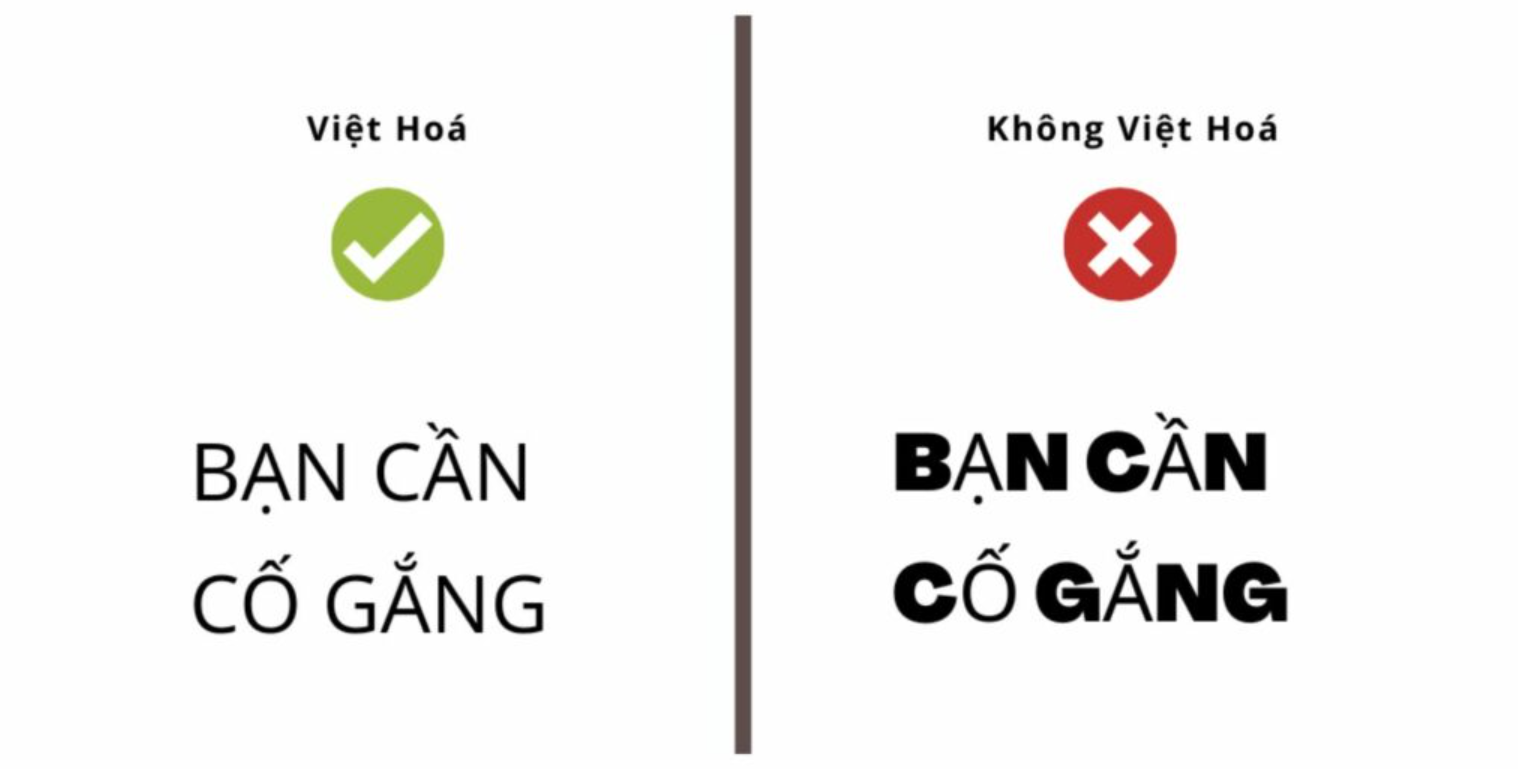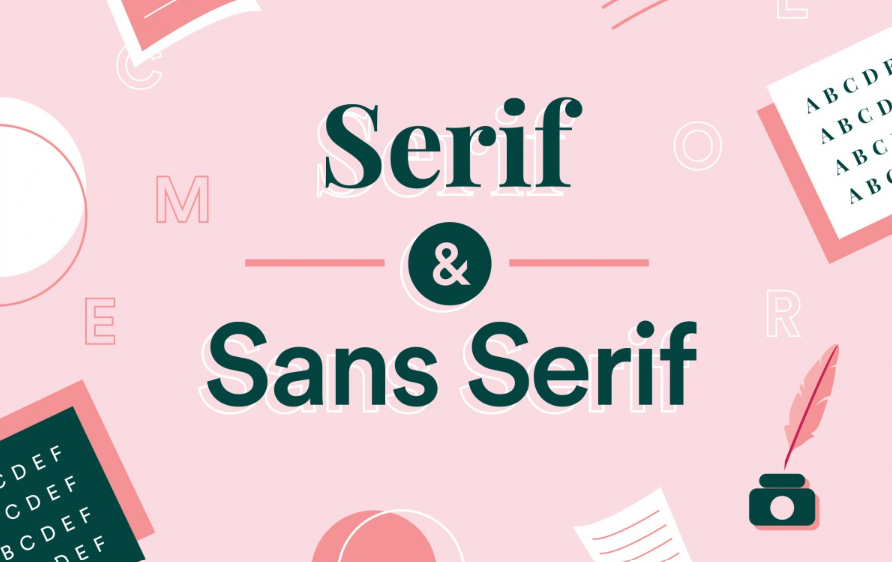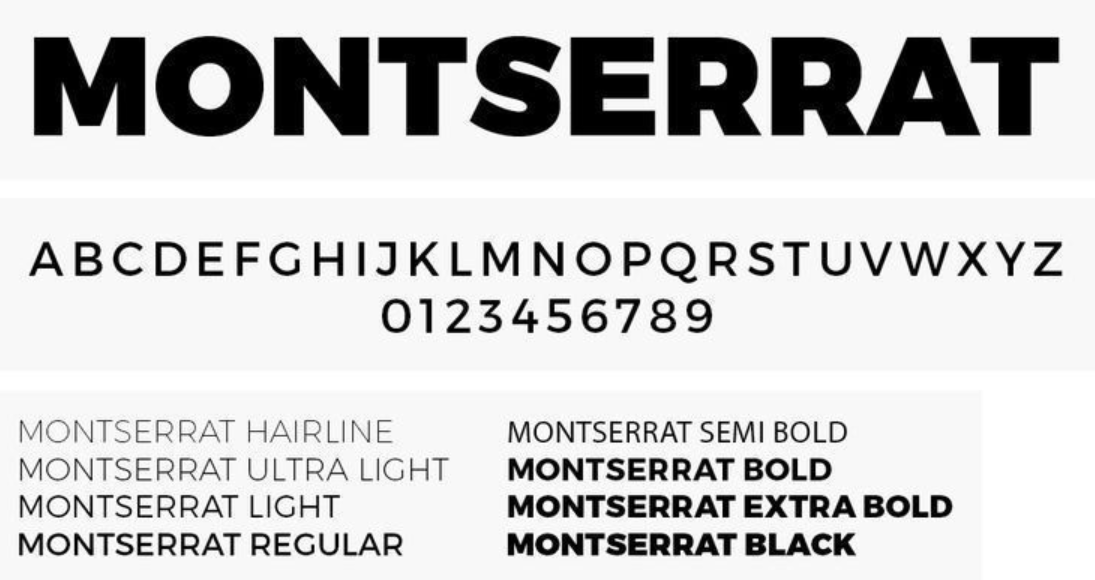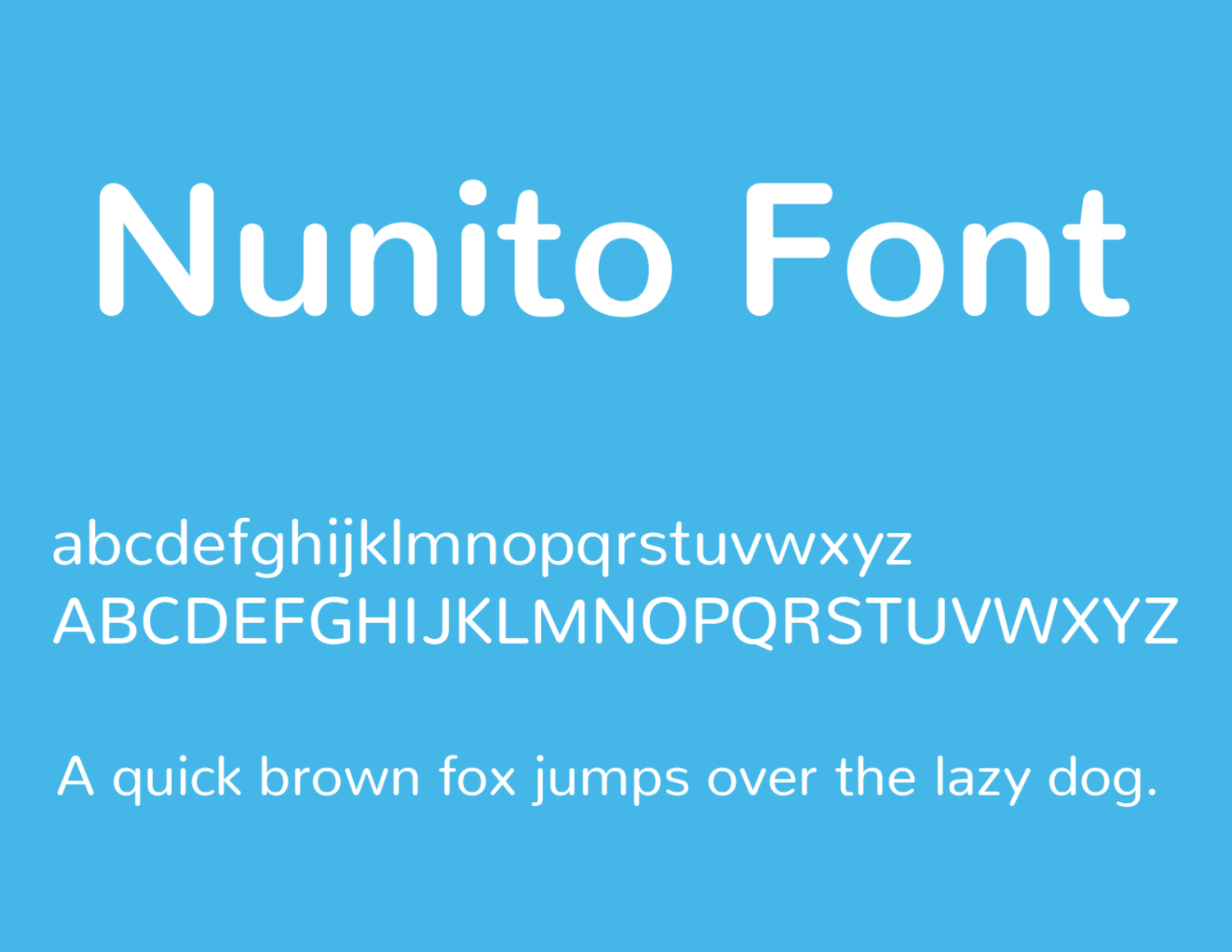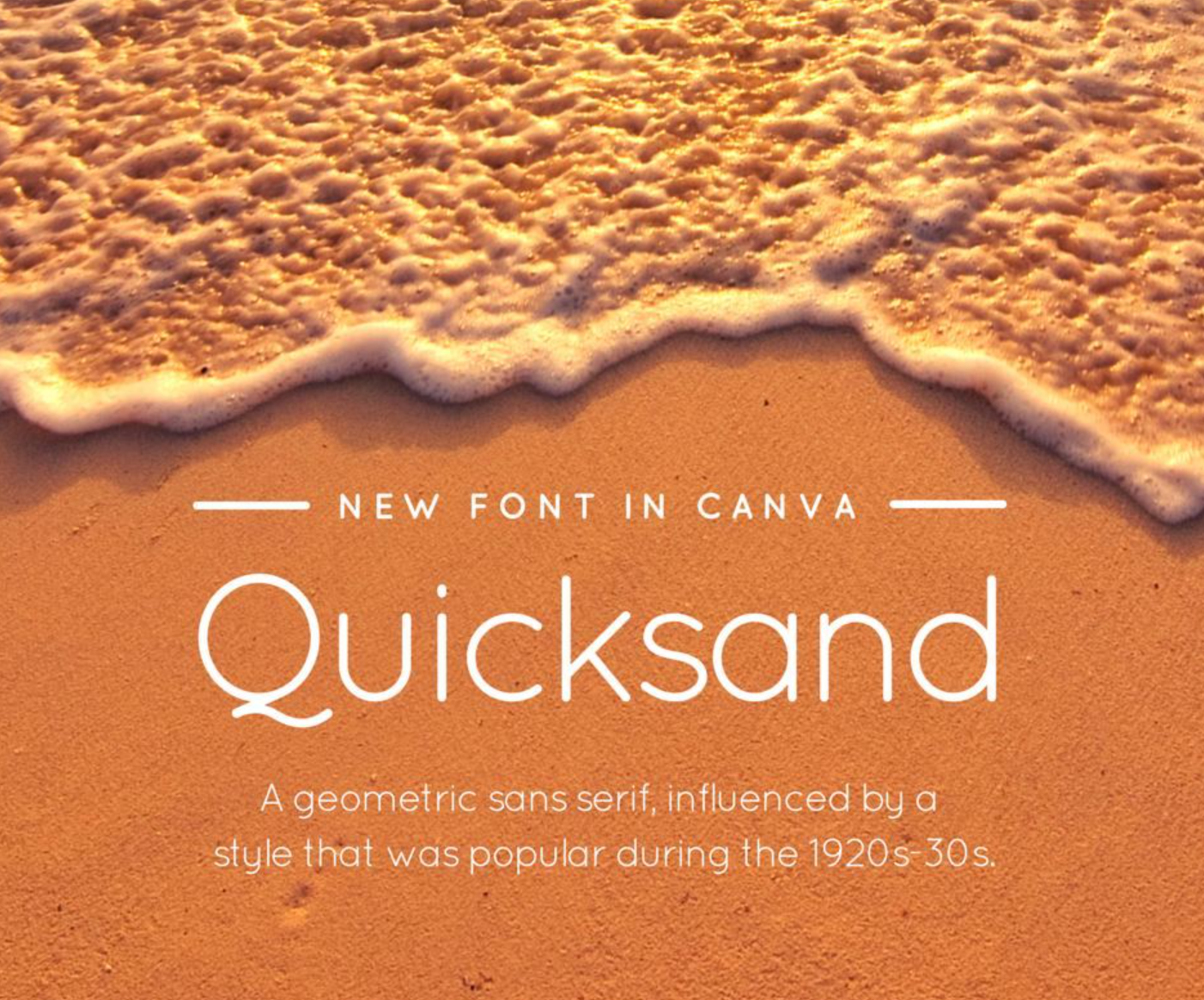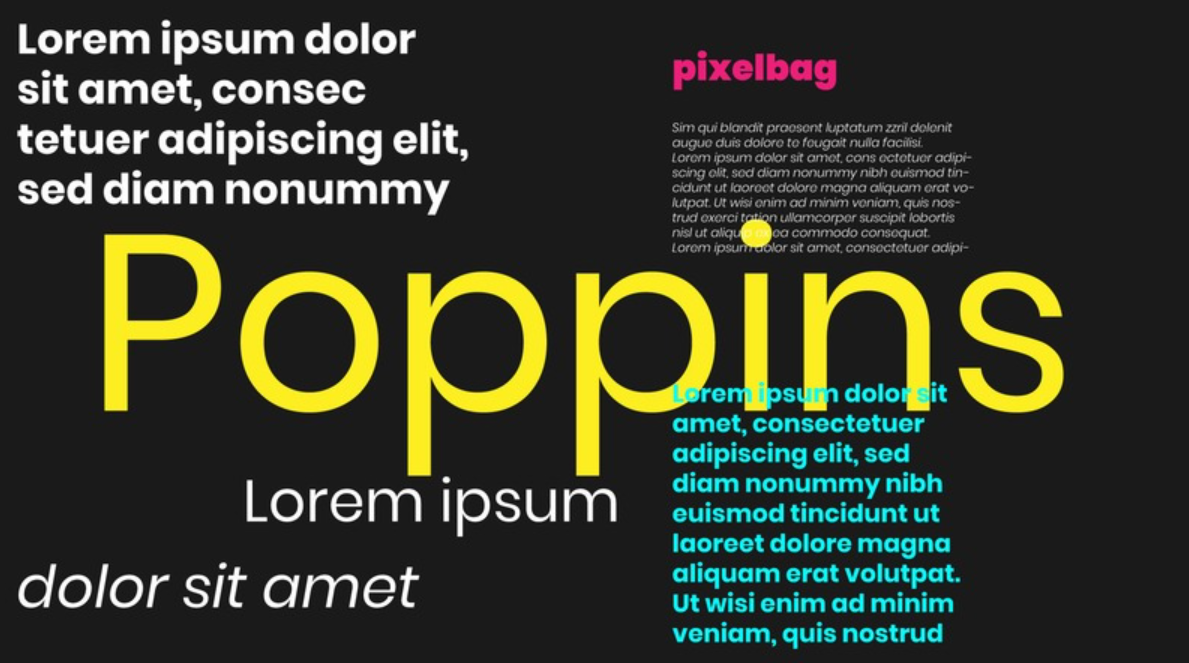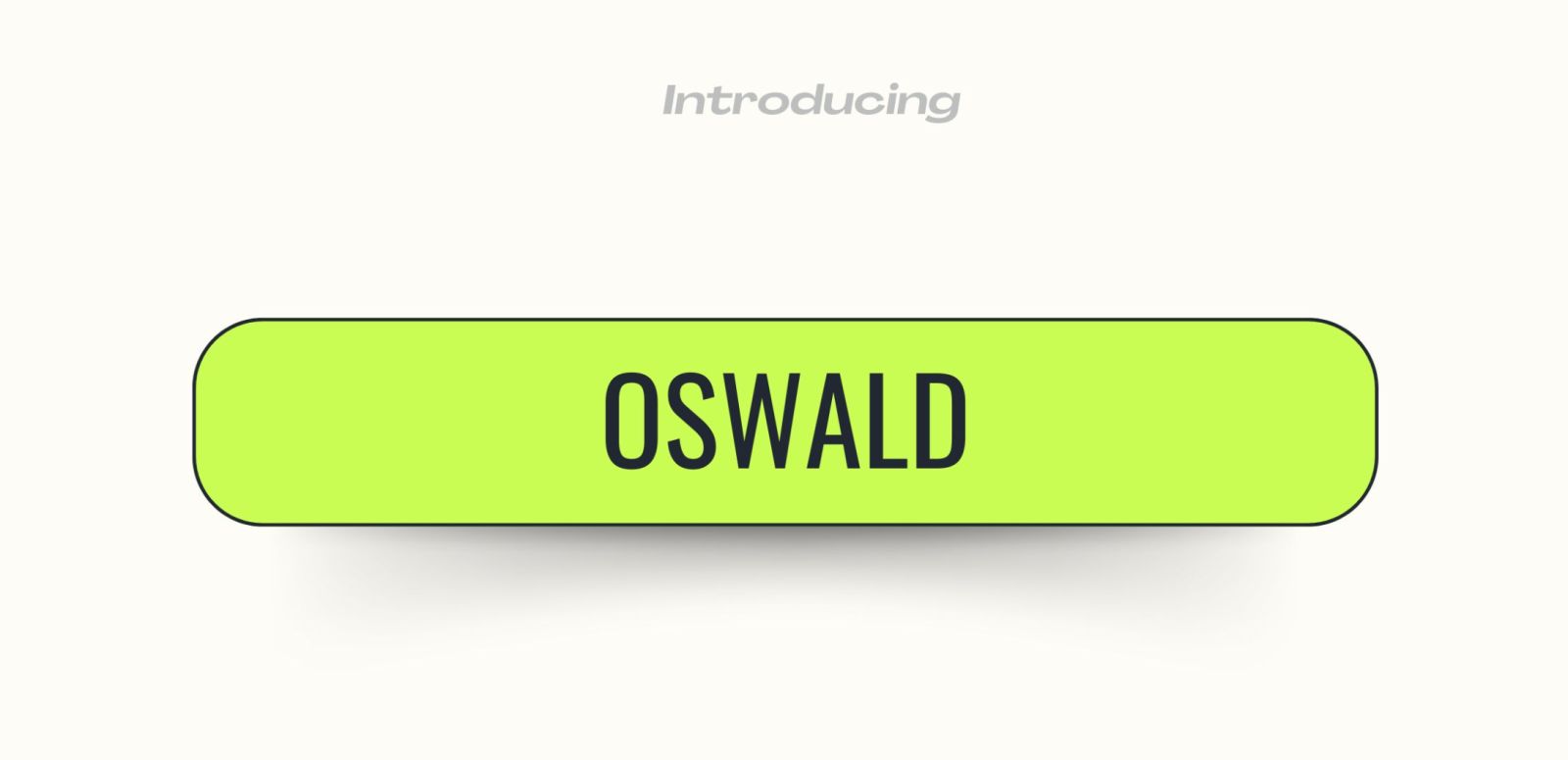
Khám Phá Kho Font Việt Hóa Miễn Phí Trên Canva
Bạn có biết rằng Canva cũng có rất nhiều phông chữ đẹp trên canva và phù hợp để bạn lựa chọn? Nếu bạn chưa biết, hãy cùng SaDesign khám phá những font chữ Việt hóa trên Canva trong bài viết này.
Bạn đang thiết kế trên Canva nhưng loay hoay mãi vì không tìm được font chữ hỗ trợ tiếng Việt đẹp mắt, đúng “gu” thẩm mỹ? Đừng lo! Việc tìm kiếm font Việt hóa miễn phí trên Canva giờ đây không còn là nỗi trăn trở như trước. Trong bài viết này, SaDesign sẽ giúp bạn tổng hợp những font chữ Việt hóa chất lượng cao, hoàn toàn miễn phí và có thể sử dụng trực tiếp trên Canva. Hãy cùng khám phá ngay để chọn được font chữ ưng ý, giúp thiết kế của bạn trở nên nổi bật, truyền cảm hứng và thể hiện đúng tinh thần bạn mong muốn nhé!
1. Font việt hóa khác gì so với font chưa việt hóa trên Canva ?
Khi làm việc với Canva, việc lựa chọn font chữ phù hợp cho tiếng Việt có thể trở thành một nhiệm vụ không dễ dàng.
Sự khác biệt giữa font chữ Việt hóa và font chữ chưa Việt hóa không chỉ ở khía cạnh thẩm mỹ mà còn ảnh hưởng đến tính đọc được và chất lượng của thiết kế.
Font việt hóa Canva
Font chưa việt Hóa
Đã được điều chỉnh và tùy chỉnh để hỗ trợ đầy đủ các ký tự và dấu trong tiếng Việt.
Font chữ không được thiết kế để hỗ trợ tiếng Việt.
Giúp thiết kế trở nên mượt mà và chuyên nghiệp.
Khi sử dụng có thể gặp phải vấn đề trong việc hiển thị các chữ cái có dấu.
Hỗ trợ đầy đủ ký tự tiếng Việt, thể hiện đúng ý muốn của người thiết kế, mang tính thẩm mỹ cao.
Thích hợp cho việc thiết kế văn bản tiếng Anh hoặc các ngôn ngữ không dùng dấu.
Số lượng font chữ Việt hóa có thể hạn chế, đòi hỏi tìm kiếm và cài đặt từ nguồn đáng tin cậy.
Không hỗ trợ đầy đủ ký tự tiếng Việt, gây rối và mất tính thẩm mỹ trong việc hiển thị văn bản tiếng Việt.
2. Mẹo sử dụng Sans Serif & Slab Serif để tìm Font chữ đẹp trên Canva
Để tìm được font chữ đẹp trên Canva, bạn nên dùng cặp từ khóa Sans Serif & Slab Serif khi tìm kiếm để nhanh chóng tìm được font chữ phù hợp:
Serif: Thường được biết đến với tên gọi “chữ có chân”, với các nét nhỏ ở cuối mỗi chữ. Chúng mang tính cổ điển và thường được sử dụng trong văn bản trang trọng hay sách giáo trình.
Sans Serif: Loại font này không có các “chân” ở cuối mỗi chữ, tạo nên vẻ ngoại hình mượt mà và hiện đại. Rất phù hợp với các thiết kế sáng tạo và trẻ trung.
Điều này giúp lọc ra các kiểu font chữ theo phong cách bạn muốn, từ đó tìm thấy các font phù hợp nhanh chóng.
Ngoài ra, đừng ngần ngại thử nghiệm nhiều kiểu font khác nhau trên bản thiết kế của bạn. Canva cho phép thay đổi font chữ một cách dễ dàng, vì vậy hãy thử nghiệm từng font một để xác định được font nào là phù hợp nhất.
3. Top font chữ tiếng việt đẹp trên canva mà bạn nên thử
Dưới đây là gợi ý các font việt hóa Canva đẹp được nhiều người yêu thích:
Montserrat: được thiết kế với đường nét chắc chắn, cân xứng, giúp font chữ này trở nên cứng cáp và dễ đọc. Phù hợp cho việc thiết kế banner hay truyền tải thông điệp một cách rõ ràng.
Nunito: với đường nét tròn trịa và mềm mại, rất thích hợp cho việc trình bày nội dung trực quan hoặc các sản phẩm dành cho trẻ em.
Lato: mang đến sự thanh thoát và tinh tế qua đường nét cân đối và chắc chắn của mình. Lato đặc biệt phù hợp cho bao bì sản phẩm, tiếp thị hoặc các ấn phẩm chuyên nghiệp.
Oswald: nổi bật với phong cách hiện đại mang hơi hướng cổ điển, đây là lựa chọn hoàn hảo cho tiêu đề bài viết, poster,… hoặc nơi bạn muốn tạo dấu ấn mạnh mẽ
Poppins: sở hữu đường nét rõ ràng và đều đặn, mang đến một phong cách thanh lịch và hiện đại. Font này được ưa chuộng trong việc thiết kế slide, trang web và ứng dụng trên điện thoại.
Quicksand: với phong cách đặc trưng là nhẹ nhàng và phóng khoáng, rất thích hợp cho các dự án trong lĩnh vực giáo dục hay những sản phẩm muốn thể hiện sự tươi mới.
Đây chỉ là một số phông chữ tiêu biểu, nhưng còn rất nhiều lựa chọn khác đang chờ bạn khám phá.
4. Kinh Nghiệm Tìm Kiếm Font Việt Hoá Trên Canva
Để tìm kiếm những font chữ tiếng Việt được Việt hoá trên Canva, bạn có thể áp dụng một số mẹo nhỏ sau:
Sử dụng hai từ khóa “Sans Serif” và “Slab Serif” khi tìm kiếm phông chữ. Đây là hai loại phông chữ không có serif, tức là không có những nét nhỏ ở cuối các thành phần của chữ. Những phông chữ này thường có thiết kế đơn giản, hiện đại và phù hợp cho nhiều loại thiết kế khác nhau.
Tránh sử dụng những phông chữ có thiết kế quá phức tạp, hoa văn, cổ điển hay có nhiều đường cong. Những phông chữ này thường không được Việt hoá hoặc bị lỗi khi sử dụng tiếng Việt. Bạn nên chọn những phông chữ có hình dạng hình học, rõ ràng và dễ đọc.
Tham khảo ý kiến của những người khác về những phông chữ tiếng Việt đẹp trên Canva. Bạn có thể xem các bài viết, video hay bình luận trên mạng xã hội để biết những phông chữ nào được nhiều người yêu thích và sử dụng. Bạn cũng có thể hỏi trực tiếp những người đã thiết kế trên Canva về những phông chữ họ sử dụng.